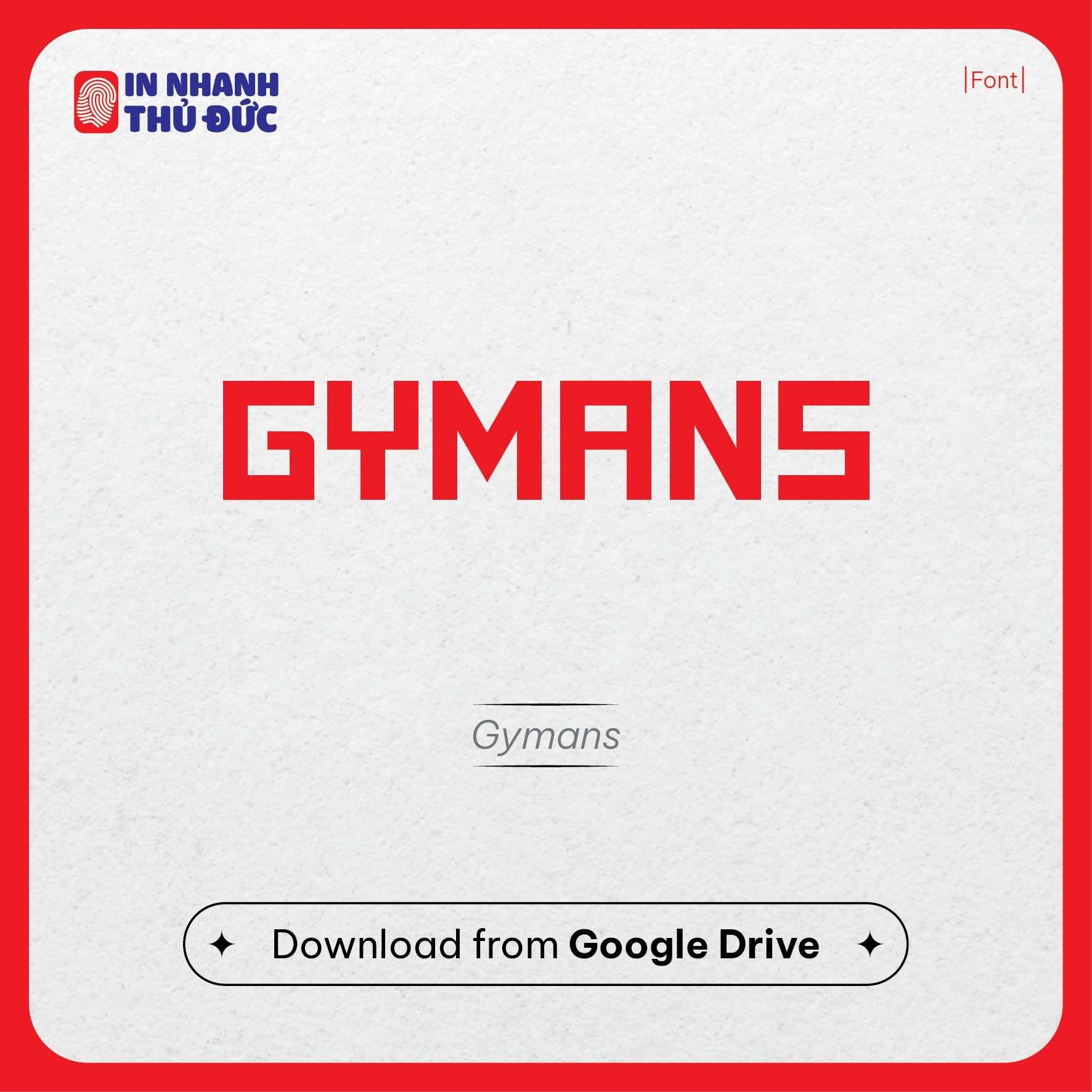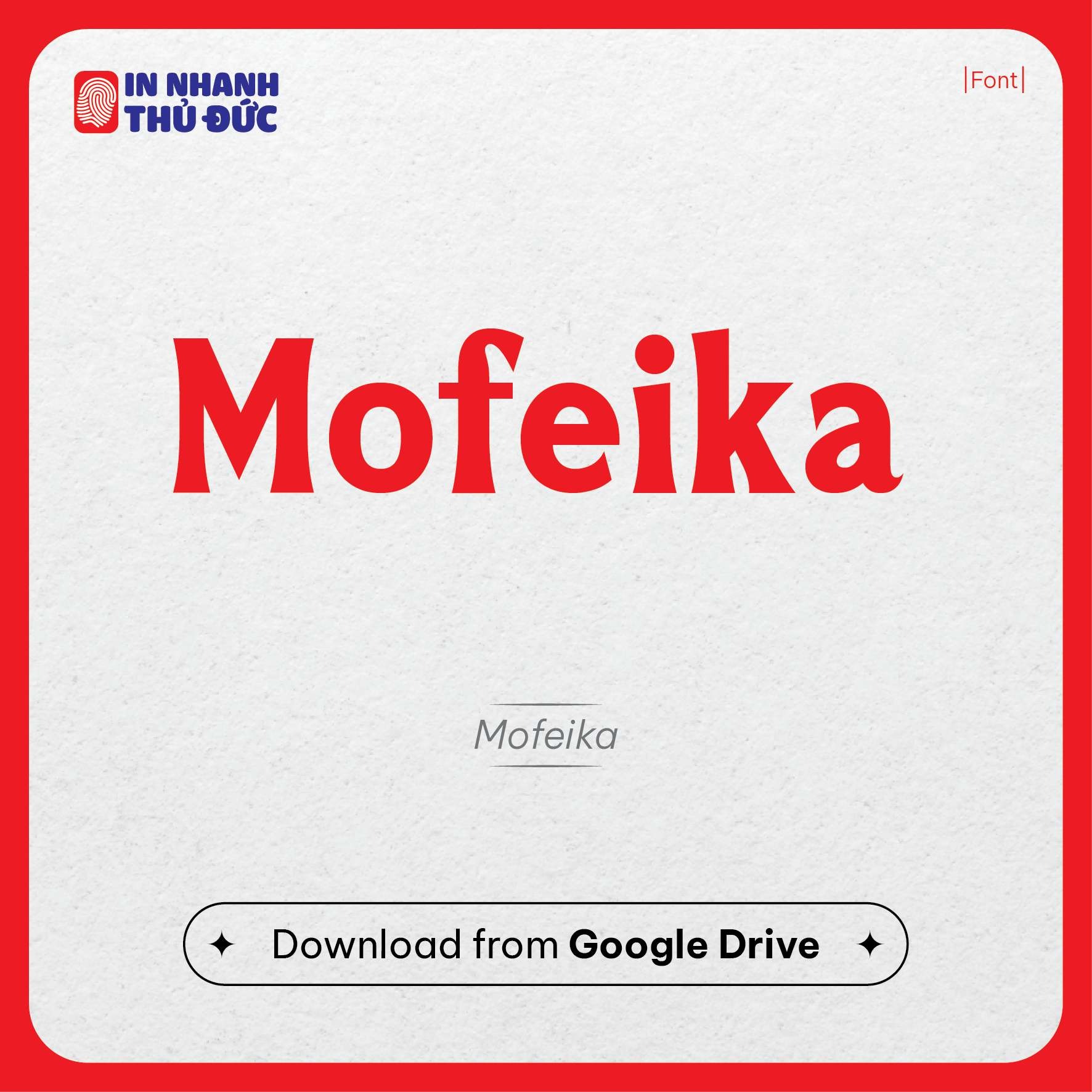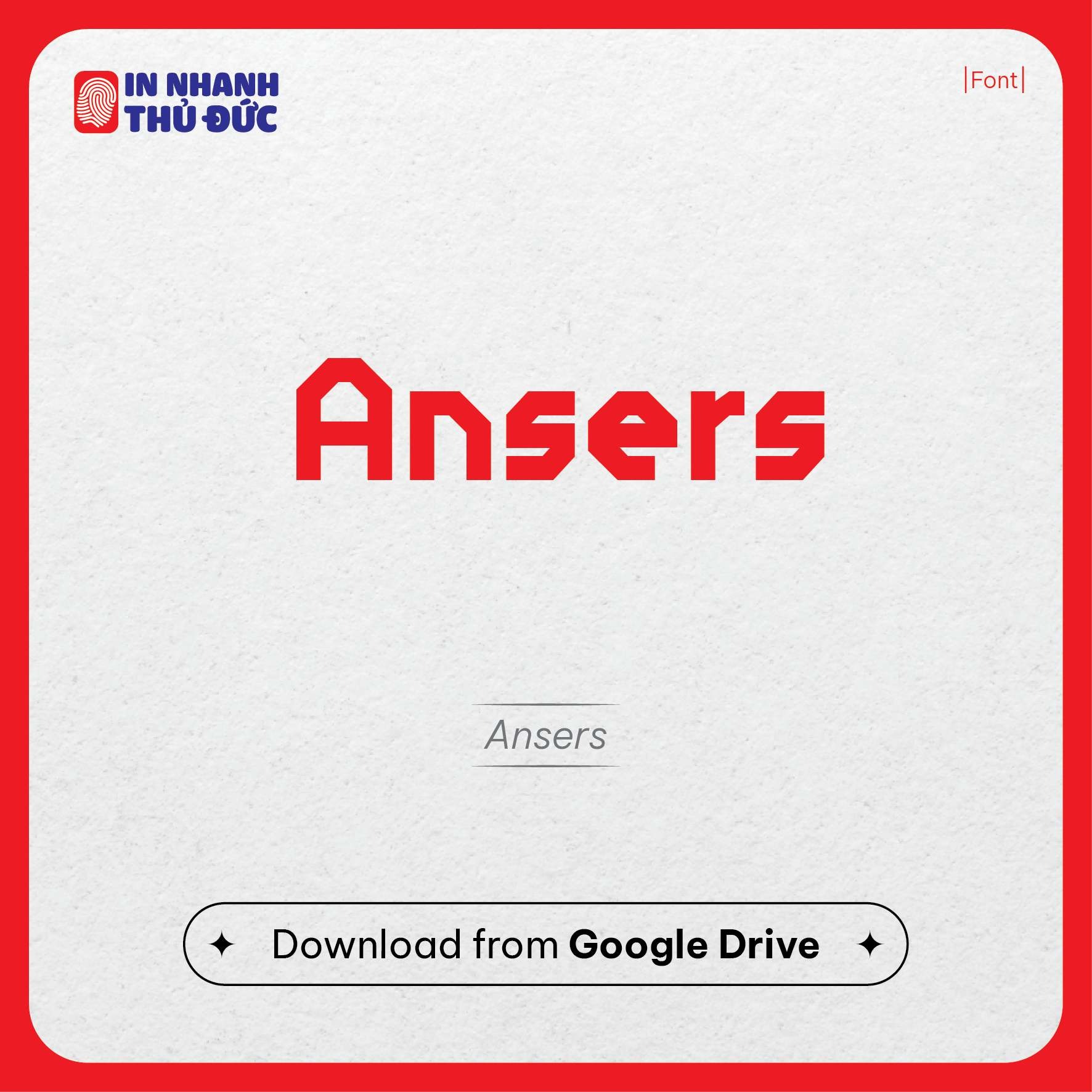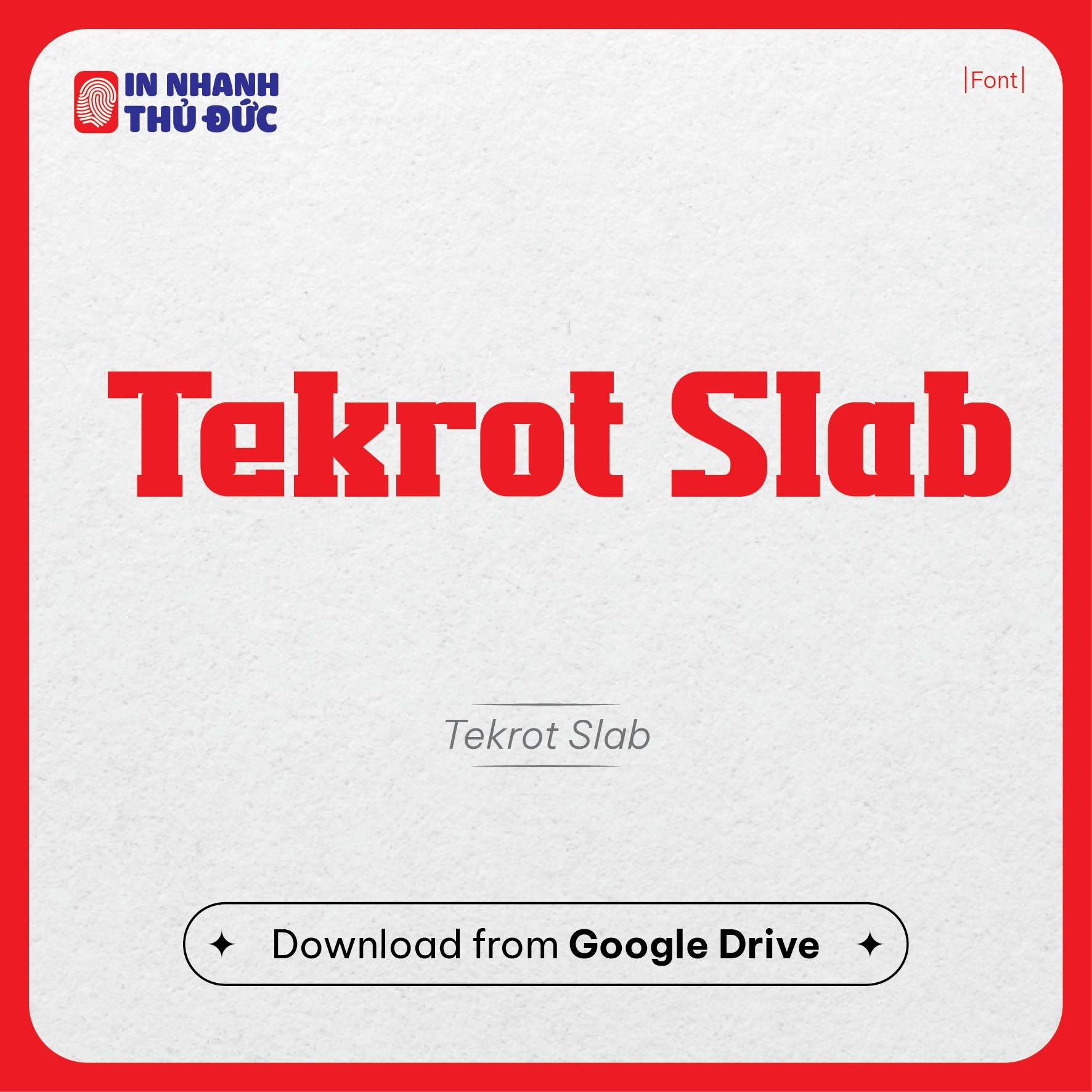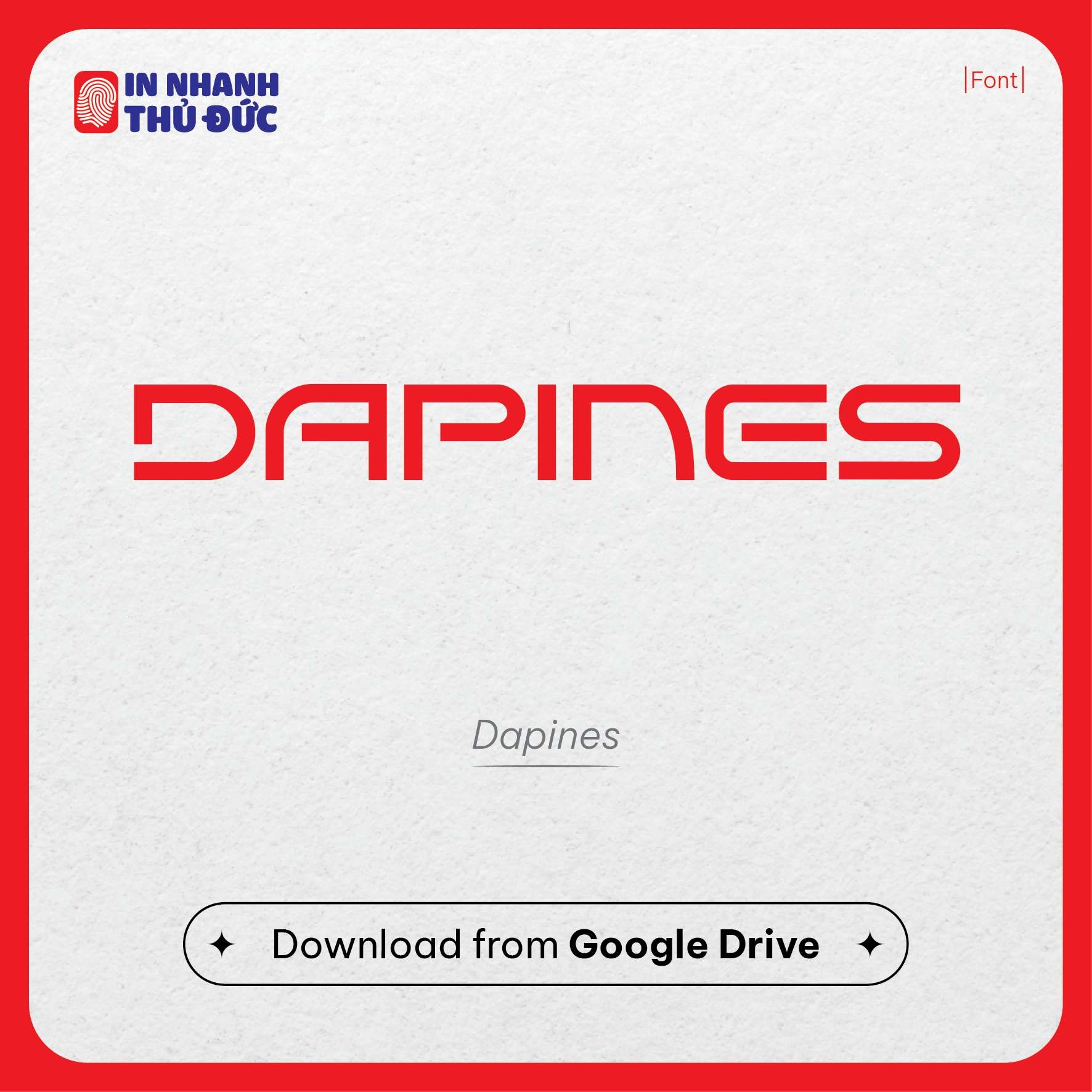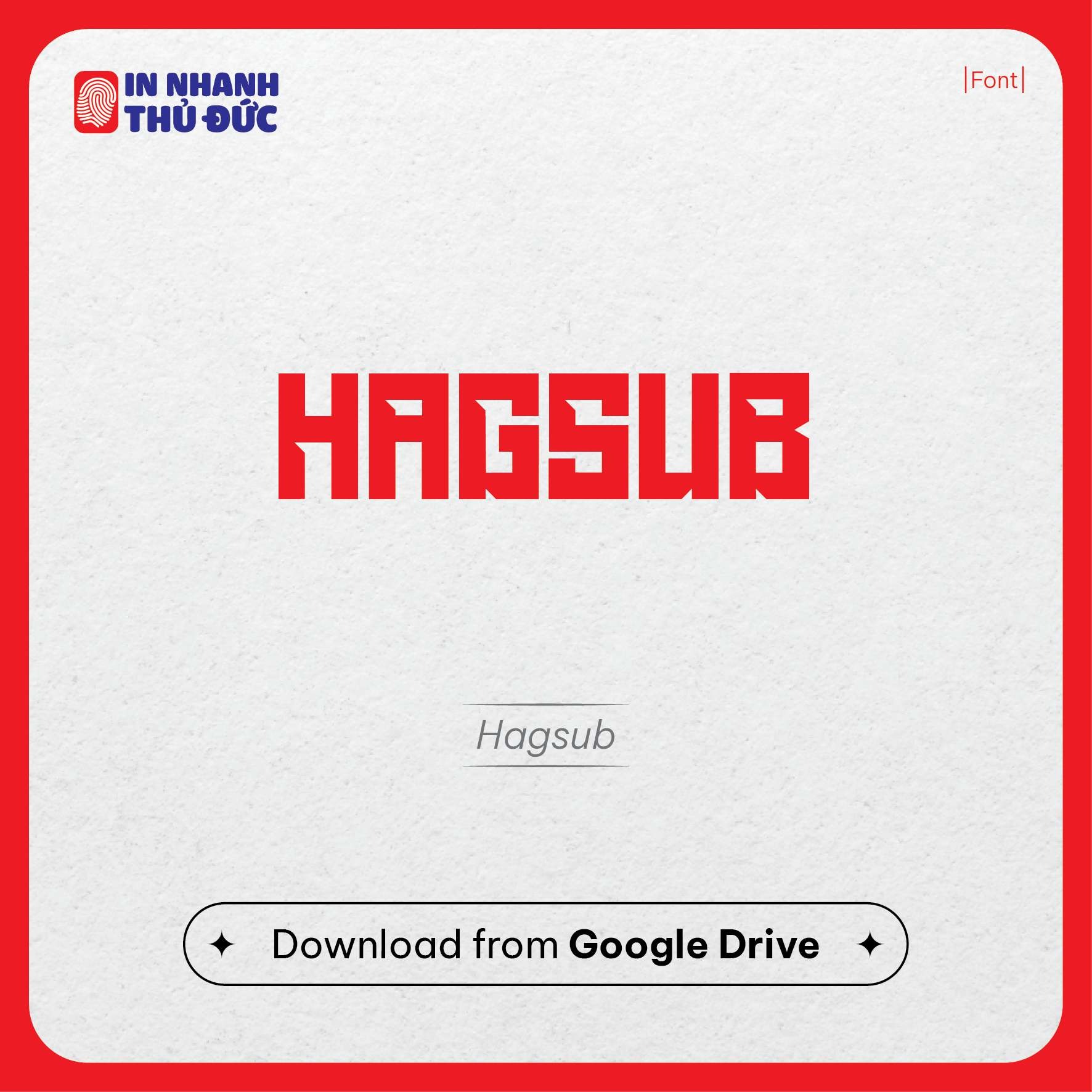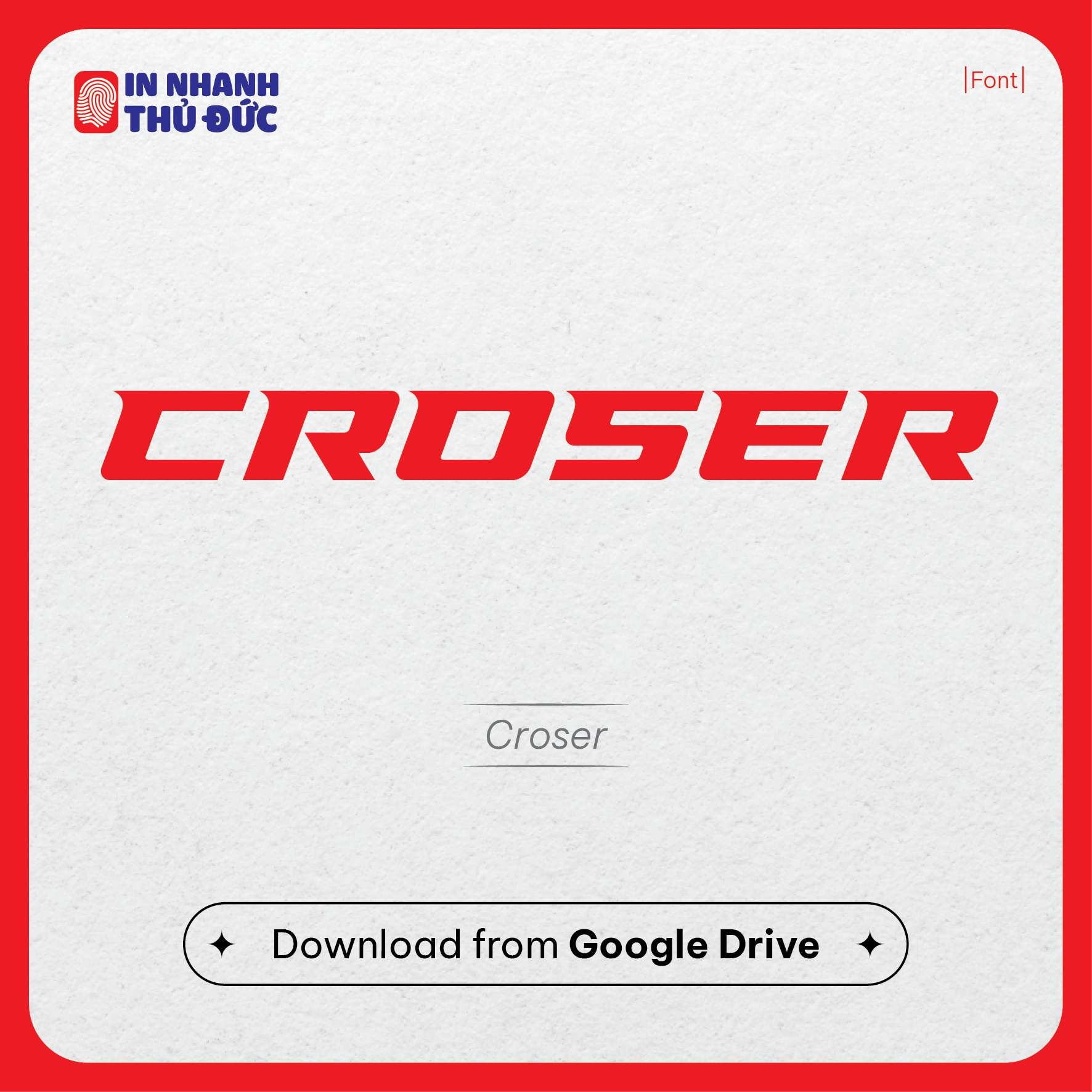
Nâng Tầm Thiết Kế: Font Chữ Thể Thao & Công Nghệ Đẹp Nhất
Trong kỷ nguyên số, ranh giới giữa thể thao và công nghệ ngày càng trở nên mờ nhạt. Từ eSports bùng nổ đến các ứng dụng theo dõi luyện tập, từ thiết bị thông minh đến các giải đấu ảo – tất cả đều cần một ngôn ngữ hình ảnh mạnh mẽ để truyền tải thông điệp. Và font chữ chính là cầu nối, là tiếng nói thầm lặng tạo nên sự khác biệt, khẳng định cá tính và truyền tải năng lượng.
Vì Sao Font Chữ Là "Vũ Khí Bí Mật" Trong Thiết Kế Thể Thao & Công Nghệ?
- Định Hình Phong Cách: Font chữ góc cạnh, hiện đại thường gắn liền với công nghệ, sự đổi mới. Font chữ đậm, chắc khỏe lại thể hiện tinh thần thể thao, sức mạnh và sự cạnh tranh.
- Truyền Tải Năng Lượng & Tốc Độ: Cả thể thao và công nghệ đều đề cao tốc độ và sự năng động. Font chữ phù hợp sẽ khơi gợi những cảm xúc này.
- Tạo Dấu Ấn Thương Hiệu: Từ logo team eSports, tên ứng dụng, đến giao diện website công nghệ hay áo đấu cầu thủ, font chữ đặc trưng là yếu tố cốt lõi của nhận diện.
- Đảm Bảo Tính Đọc & Trải Nghiệm Người Dùng: Rõ ràng, dễ đọc trên mọi thiết bị và kích thước là yêu cầu tiên quyết, đặc biệt trong các giao diện ứng dụng hoặc thông số kỹ thuật.
Đặc Trưng Của Một Font Chữ Thể Thao - Công Nghệ Đỉnh Cao
- Hiện Đại & Tối Giản: Ưu tiên các font Sans Serif với đường nét gọn gàng, sạch sẽ.
- Mạnh Mẽ & Dứt Khoát: Độ đậm (Bold, Black) và các góc cạnh rõ ràng thể hiện sự quyết đoán. Ví dụ như GYMANS với khối chữ dày, cực kỳ vững chãi.
- Độc Đáo & Dễ Nhận Diện: Các chi tiết cách điệu tinh tế, không quá rườm rà, giúp font chữ nổi bật.
- Linh Hoạt (Versatile): Sử dụng tốt trên cả bản in (áo đấu, poster) lẫn giao diện số (website, app).
- Cảm Hứng Từ Hình Học & Không Gian: Nhiều font công nghệ có cấu trúc dựa trên các hình khối cơ bản hoặc gợi cảm giác tương lai, vũ trụ.
Khám Phá Bộ Sưu Tập Font Chữ Thể Thao & Công Nghệ Nổi Bật
Hãy cùng điểm qua những "ngôi sao" trong làng font chữ, bao gồm cả những cái tên bạn đã cung cấp:
1. Nhóm Font Sans Serif Siêu Đậm & Hiện Đại
Đây là lựa chọn hàng đầu cho các thiết kế cần sự mạnh mẽ, rõ ràng và trực diện.
GYMANS: Một ví dụ điển hình cho sức mạnh tuyệt đối. Với các ký tự được kéo giãn theo chiều ngang và độ đậm tối đa, GYMANS hoàn hảo cho các tiêu đề lớn, logo phòng gym, các sự kiện thể thao đối kháng, hoặc các thương hiệu muốn khẳng định vị thế "khổng lồ".
ENGINE: Vẫn là một lựa chọn tuyệt vời, gợi sự cơ khí, bền bỉ, phù hợp với các đội đua, công nghệ chế tạo hoặc các thiết kế cần sự vững chãi.
Mofeika: Font chữ này mang đến sự kết hợp thú vị giữa độ đậm và một chút mềm mại ở các đường cong, tạo cảm giác vừa mạnh mẽ vừa hiện đại, dễ tiếp cận. Rất thích hợp cho các thương hiệu công nghệ trẻ trung hoặc các ấn phẩm thể thao không quá "hầm hố".
Cintra & Teritone: Những lựa chọn an toàn và hiệu quả cho tính dễ đọc và vẻ ngoài chuyên nghiệp, phù hợp cho cả tên cầu thủ, menu ứng dụng, hoặc các khối văn bản trong thiết kế.
2. Nhóm Font Cách Điệu, Mang Đậm Dấu Ấn Tương Lai
Những font này thường có những đường cắt, nối độc đáo, gợi cảm giác tốc độ, đột phá, rất hợp với eSports và các công ty công nghệ tiên phong.
Crosser: Thiết kế táo bạo, không gian âm thông minh, cực kỳ phù hợp cho các thương hiệu eSports, game, hoặc các sản phẩm công nghệ vũ trụ.
Dapines: Với các nét đứt đoạn đặc trưng, Dapines mang lại vẻ ngoài công nghệ cao, như một mạch điện tử, lý tưởng cho các dự án liên quan đến AI, dữ liệu hoặc truyền thông số.
Hagsub: Vẫn là biểu tượng của sức mạnh và sự bí ẩn, font chữ này có thể được ứng dụng trong các thiết kế game, các đội tuyển có linh vật mạnh mẽ, hoặc các sản phẩm công nghệ bảo mật.
3. Nhóm Font "College" Biến Tấu Hiện Đại
Vẫn giữ tinh thần truyền thống của thể thao học đường, nhưng được làm mới bằng các đường nét gọn gàng hơn, phù hợp với cả các ứng dụng công nghệ giáo dục hoặc các nền tảng thể thao trực tuyến.
- Ví dụ tham khảo: Các biến thể của Bebas Neue, Montserrat với độ đậm cao, hoặc các font như Akira Expanded.
- Ứng dụng: Logo các giải đấu sinh viên, các nền tảng học trực tuyến về thể thao, thiết kế áo thun cho các câu lạc bộ.
Bí Quyết Vàng Để Chọn Font Chữ "Đo Ni Đóng Giày"
- Thấu Hiểu Thương Hiệu: Phong cách của bạn là gì? Năng động, chuyên nghiệp, đột phá hay thân thiện?
- Nghiên Cứu Đối Thủ & Xu Hướng: Xem các thương hiệu lớn trong ngành đang sử dụng font gì, nhưng đừng sao chép, hãy tìm cách tạo sự khác biệt.
- Kiểm Tra Tính Tương Thích Việt Hóa: Đối với các dự án tại Việt Nam, đảm bảo font chữ hỗ trợ đầy đủ tiếng Việt có dấu.
- Thử Nghiệm Font Ở Nhiều Kích Cỡ & Môi Trường: Font chữ phải đẹp và dễ đọc trên màn hình điện thoại, website, áo thun, và cả billboard quảng cáo.
- Cân Nhắc Sự Kết Hợp: Chọn một font chính ấn tượng cho tiêu đề và một font phụ dễ đọc hơn cho nội dung để tạo sự cân bằng.